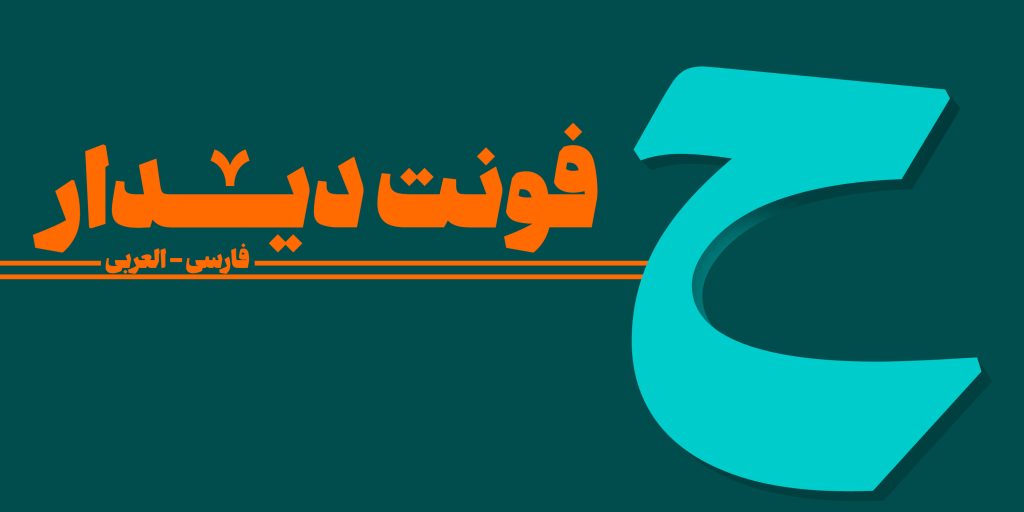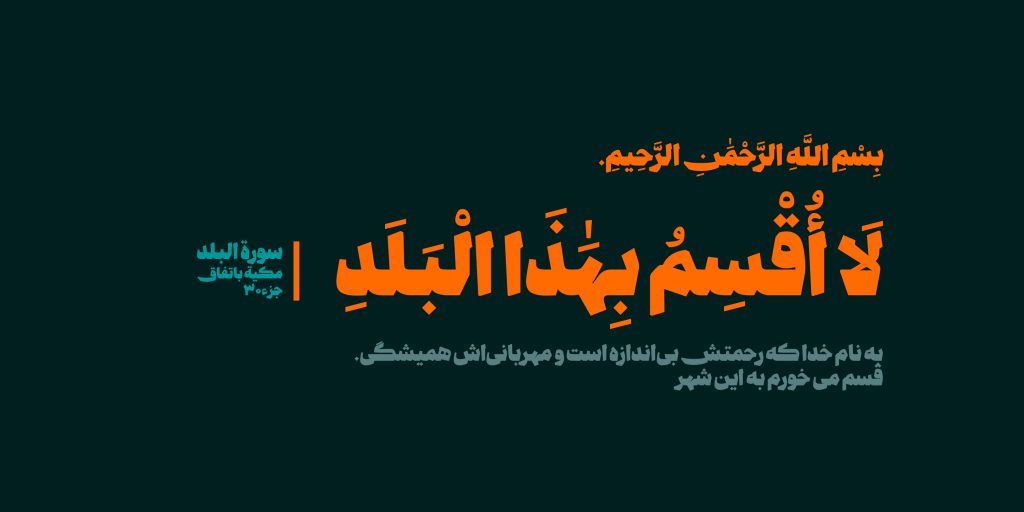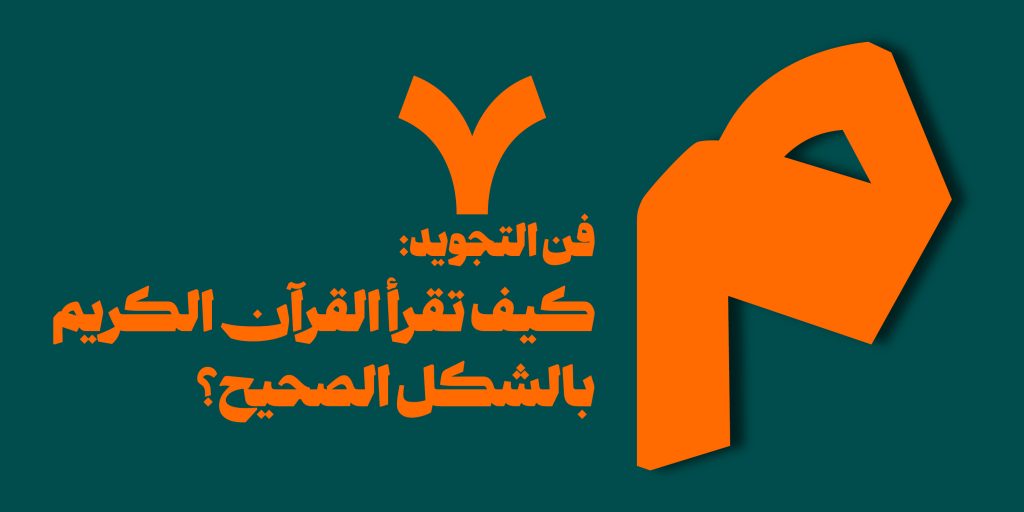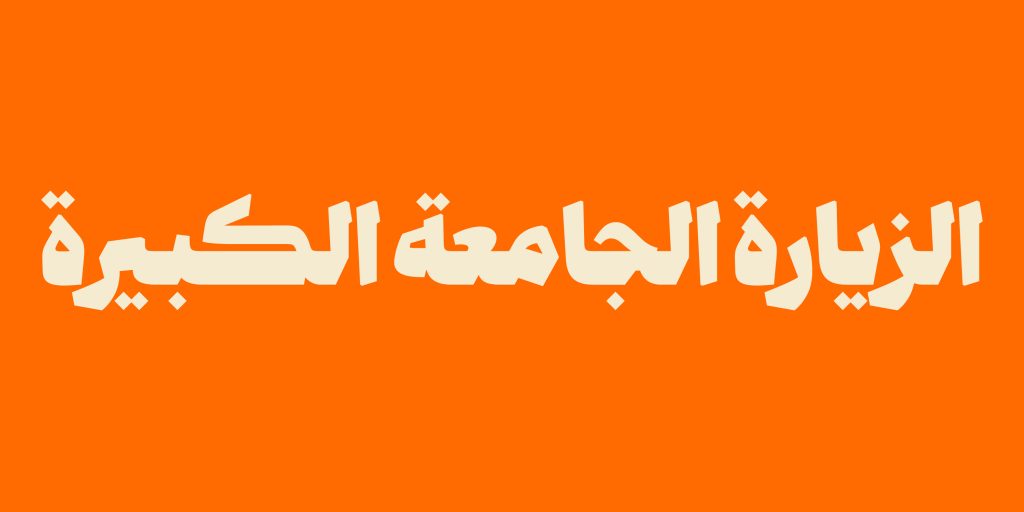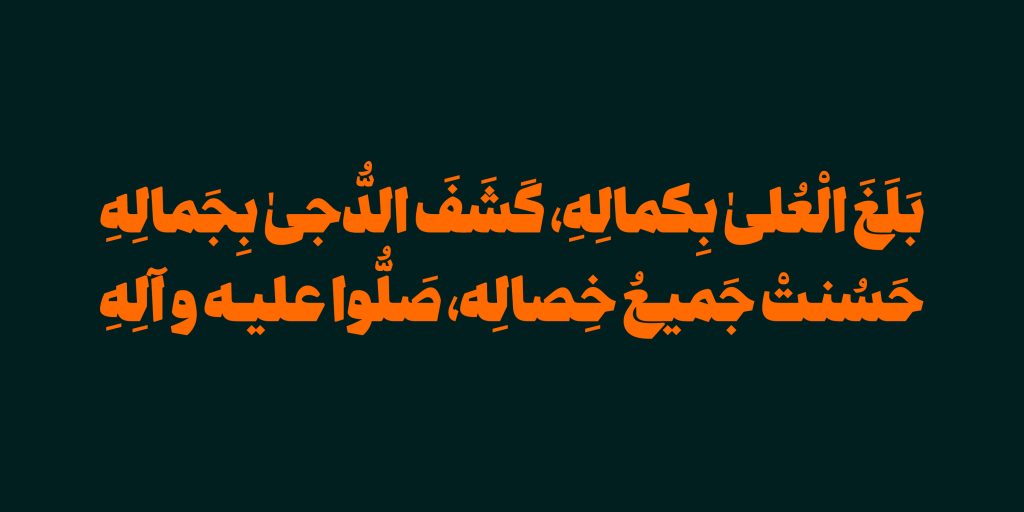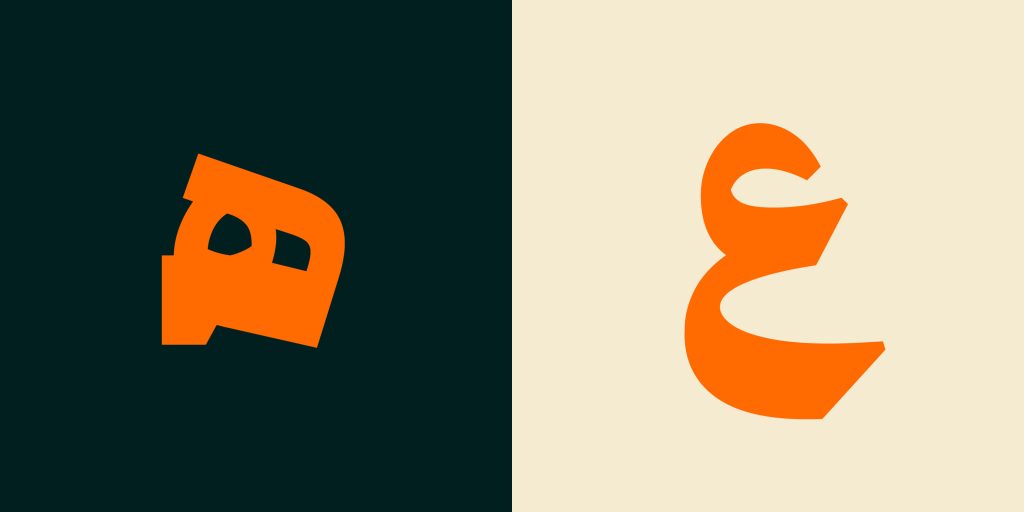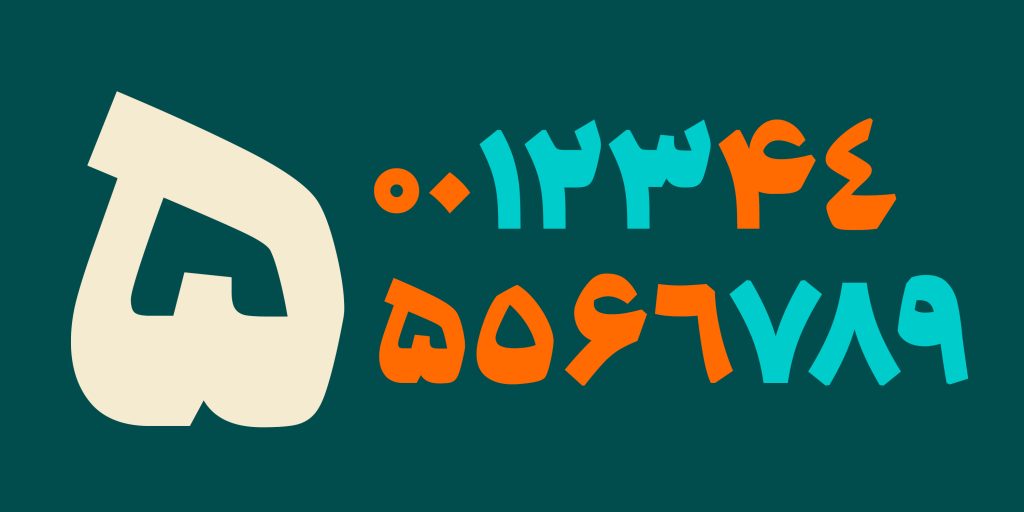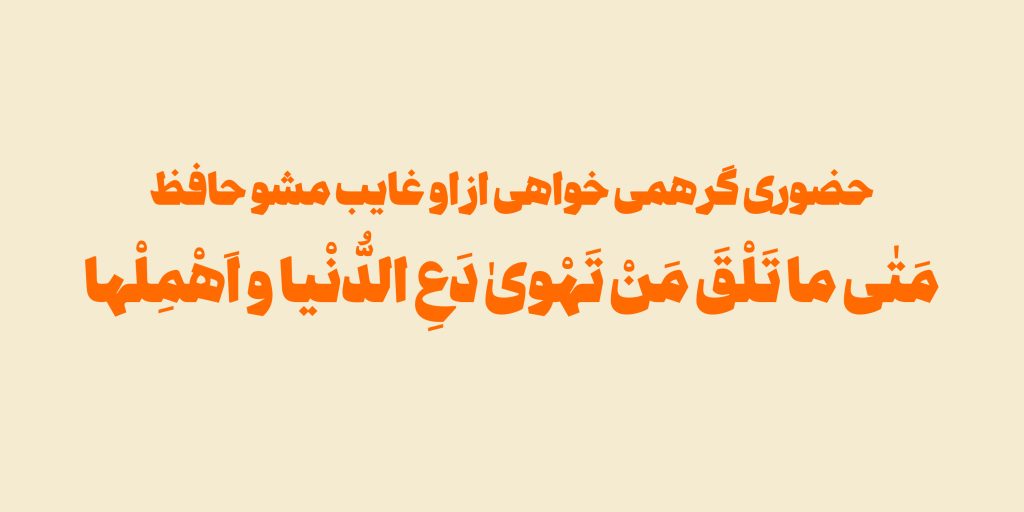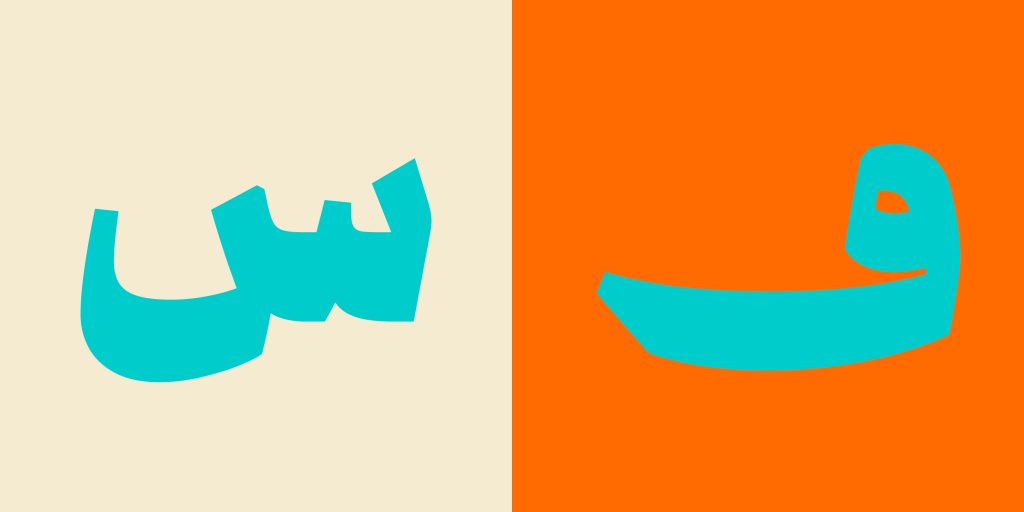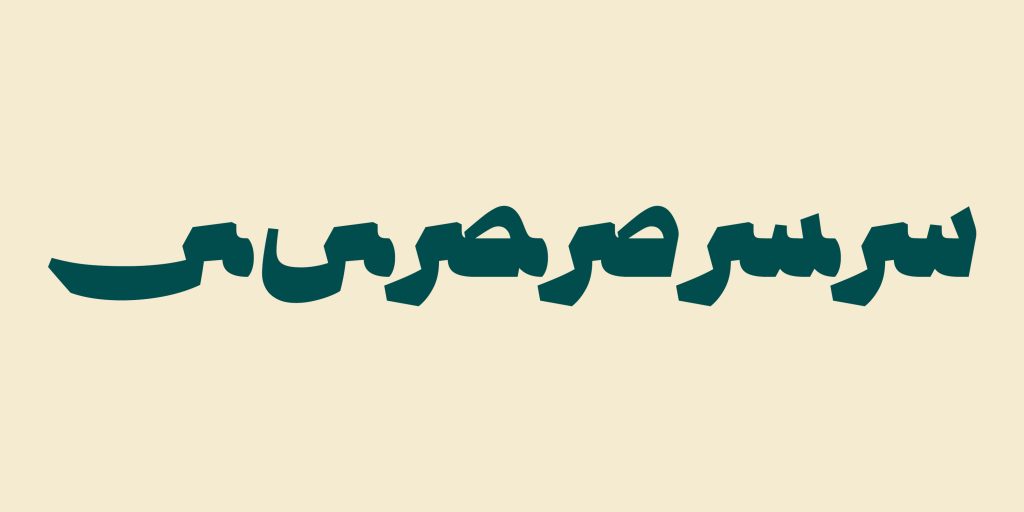
فونت دیدار – قلمی مناسب عناوین و تیتر ها
فونت دیدار با الهام از زیباییهای خط نسخ و ساختاری محکم و استوار طراحی شده است. این فونت، با کرسی ضخیم و حضور پررنگی که در صفحه دارد، گزینهای ایدهآل برای تیترهای جدی و رسمی است.
دیدار نهتنها اقتدار و صلابت را در نگاه اول القا میکند، بلکه با رعایت تناسبات دقیق و وزن سنگین، حس اعتماد و اعتبار را نیز به محتوای شما میافزاید.
فرمهای هندسی سنجیده و ضرباهنگ متعادل در حروف، باعث شدهاند تا این فونت در عین سادگی، نمایشی باشکوه و جدی از متن ارائه دهد.
اگر به دنبال فونتی هستید که در تیترها، بیهیچ تزلزلی، ایستادگی و جدیت را فریاد بزند، دیدار انتخابی شایسته است.
فارسی، عربی
1 وزن